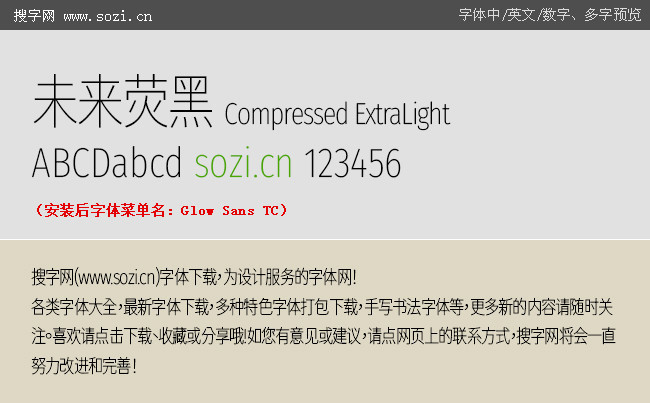
未來(lái)熒黑GlowSansTC-Compressed-ExtraLight
搜字網(wǎng)給大家提供一款未來(lái)熒黑GlowSansTC-Compressed-ExtraLight中文字體下載,未來(lái)熒黑-Compressed版是未來(lái)熒黑中的一個(gè)瘦長(zhǎng)體系列,未來(lái)熒黑是一個(gè)基于思源黑體、Fira Sans和Raleway的開(kāi)源字體項(xiàng)目,該字體由八種字重,字體中宮與字面更加收斂,細(xì)節(jié)上面處理更加的干練,適合應(yīng)用于藝術(shù)設(shè)計(jì)、平面宣傳設(shè)計(jì)、網(wǎng)頁(yè)設(shè)計(jì)等廣告設(shè)計(jì)。